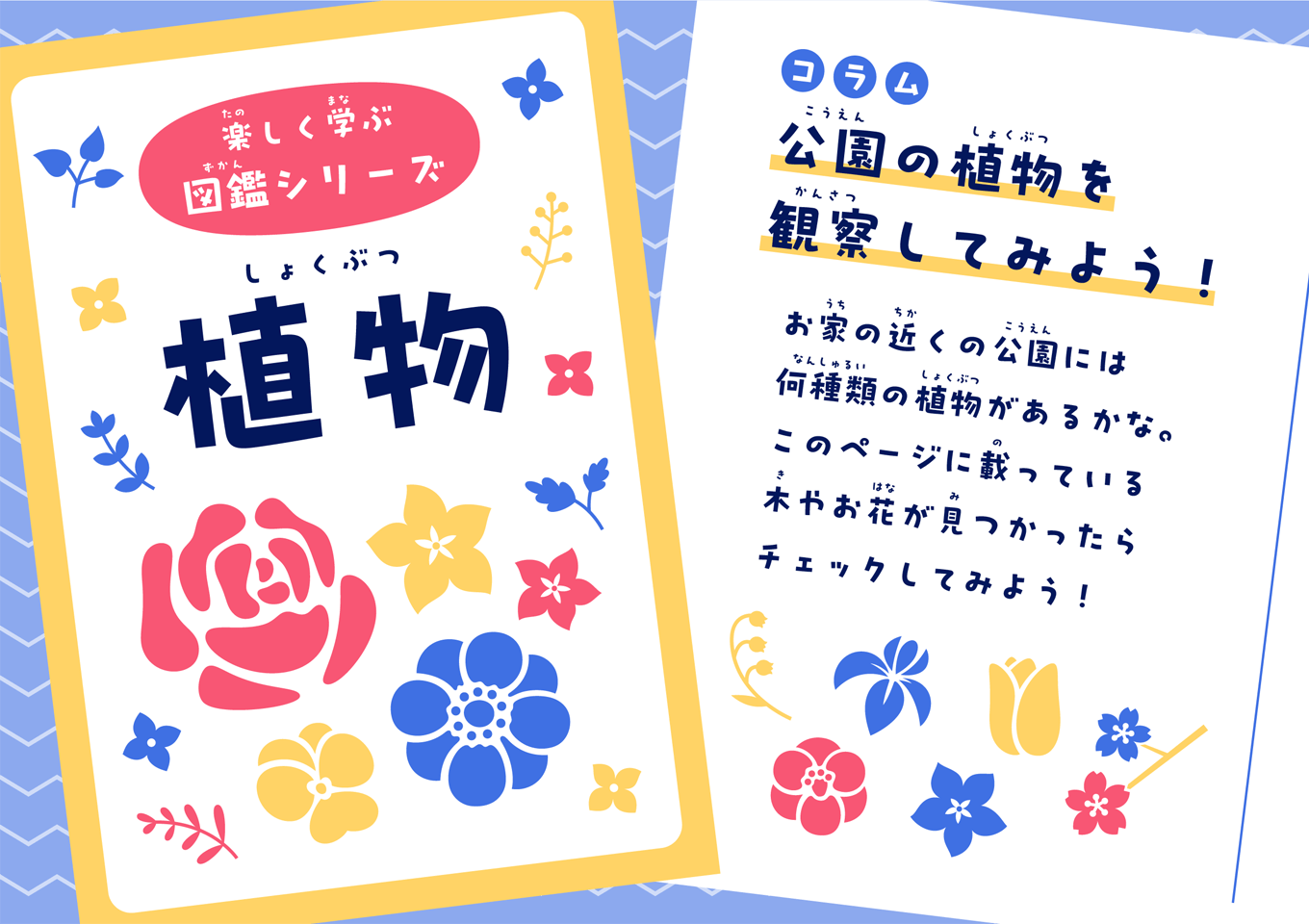
「プフ」シリーズは、統一しすぎない自由な字形と小さめの字面が特徴のデザイン書体ラインナップです。「プフ ポッケ」は、ゴシック体風のデザインをベースに上の折り返しにカーブのアクセントを取り入れ、パッケージやキャプションなどで力の入りすぎない可愛らしさを表現することができます。また、書体のキャラクターを表すオリジナル絵文字を1文字搭載しており、異体字として選択入力が可能です。